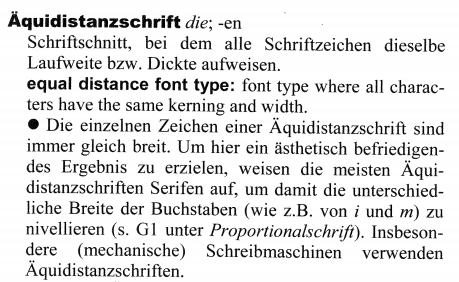
Habt ihr schon mal den Ausdruck Äquidistanzschrift für eine nicht-proportionale Schrift gehört? Mir war der Begriff völlig neu. Gefunden habe ich ihn im Wörterbuch zur Lexikographie und Wörterbuchforschung:
Es gibt wohl noch mehr Begriffe dafür:
• Festschrittschrift
• Festbreitenschrift
• Konstantschrift
• Monospace
• Fixed Font
• Teletype
„Teletype“ gibts noch in den LaTeX-Befehlen \texttt und \ttfamily.